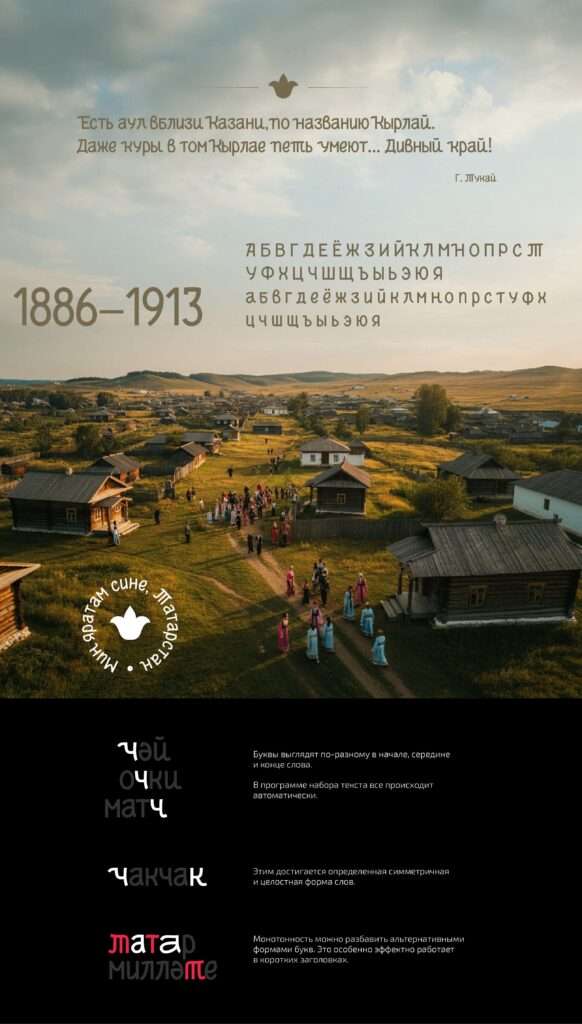
Милләт. Татарский кириллический шрифт
Язык — это живой организм, в котором каждая буква хранит частицу души народа.
Это рассказ о том, как татарская идентичность формировалась и преобразовывалась сквозь века, оставляя след в каждой строчке истории. Буквы, сменяя обличья, объединяются в единое целое, символизируя неразрывную связь прошлого и будущего, где каждый голос имеет значение.